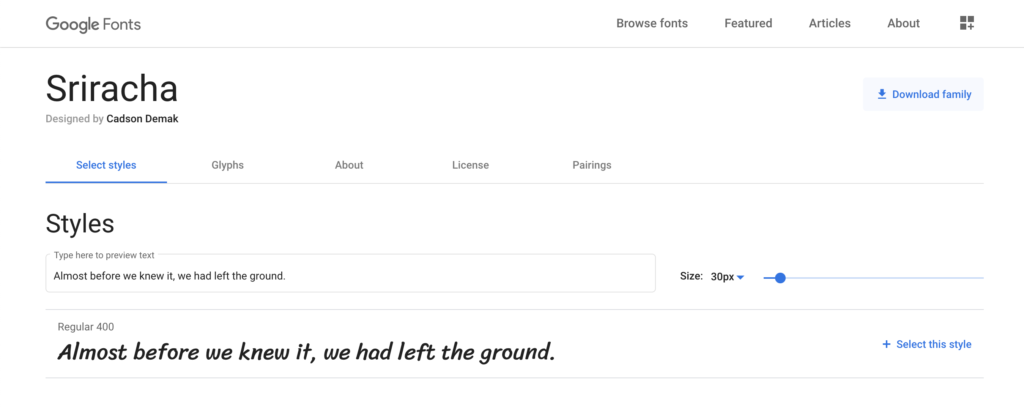
มองหาฟอนต์ภาษาไทยสวย ๆ ใช้งานฟรี นี่เลย…ฟอนต์จาก Google Font ที่มีฟอนต์ภาษาไทยให้เลือกใช้มากมาย วันนี้ทีมงานได้คัดสรรฟอนต์นไทยมาแนะนำให้ชมกันค่ะ เผื่อจะนำไปใช้ประกอบงานส่วนตัว
แนะนำ 8 ฟอนต์ไทยสวย ๆ จาก Google Font คัดสรรมาให้ดาวน์โหลดใช้งานฟรี
ฟอนต์ (Font) ที่จะแนะนำต่อไปนี้เป็นฟอนต์ภาษาไทยที่สวยงาม ดูเป็นมิตร สามารถกับงานส่วนตัวหรือเพื่อการศึกษาได้ฟรี ส่วนงานเพื่อการค้าอาจจะต้องซื้อลิขสิทธิ์ฟอนต์นะคะ
1. Mitr [ดาวน์โหลดที่นี่]
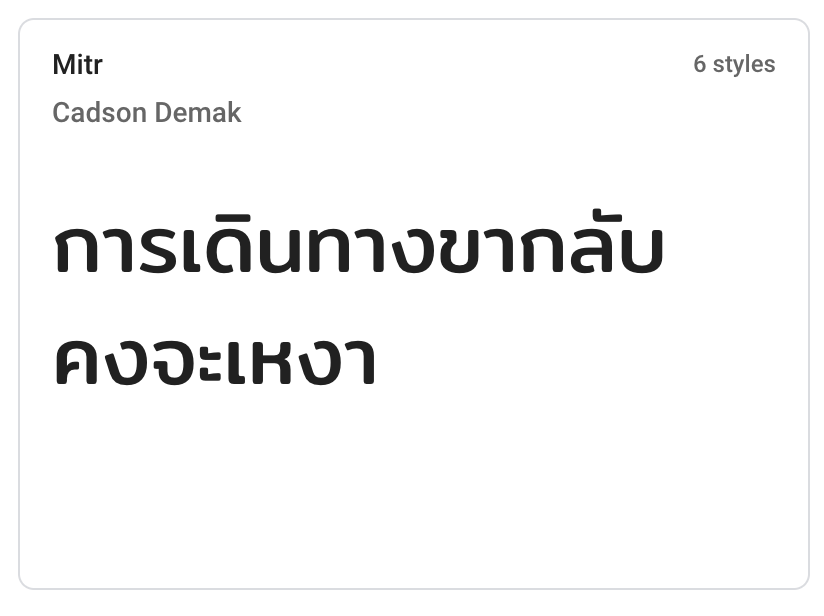
2. Chonburi [ดาวน์โหลดที่นี่]
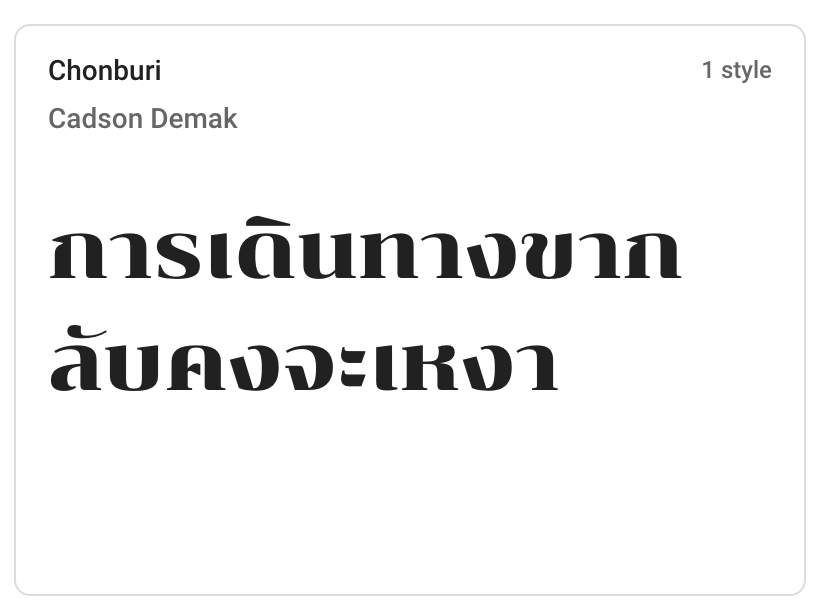
3. Sriracha [ดาวน์โหลดที่นี่]
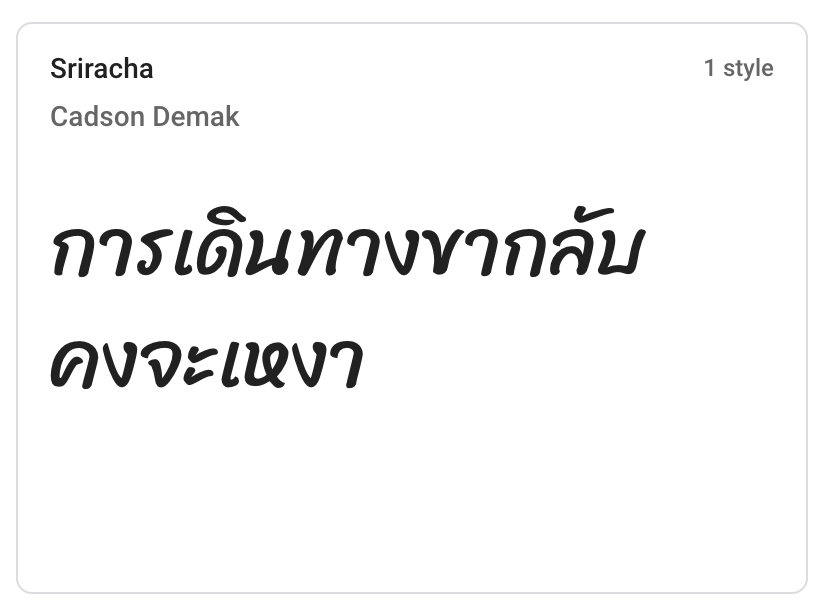
4. Kanit [ดาวน์โหลดที่นี่]
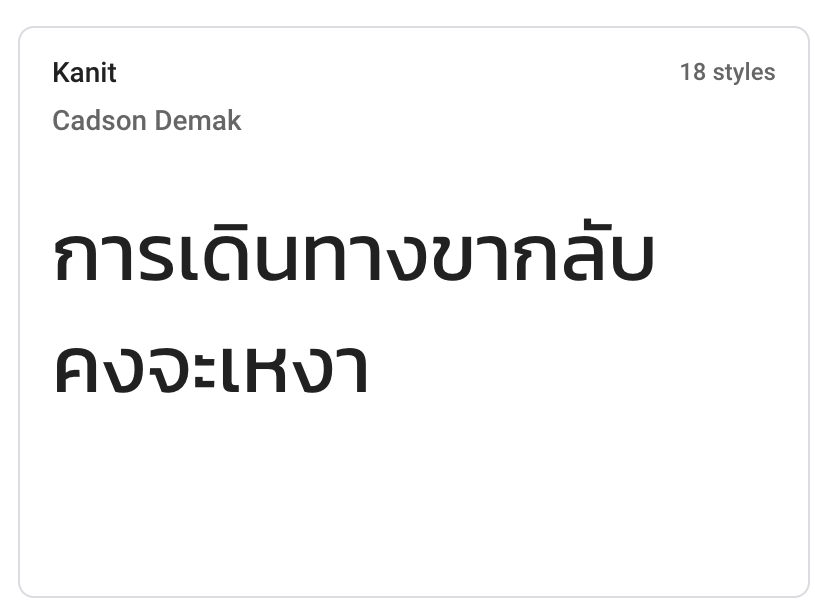
5. Itim [ดาวน์โหลดที่นี่]
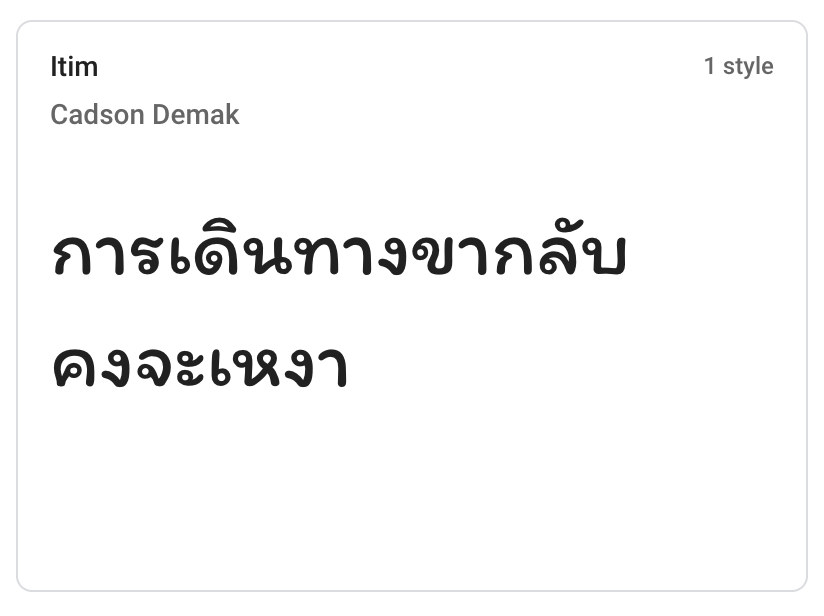
6. Pridi [ดาวน์โหลดที่นี่]
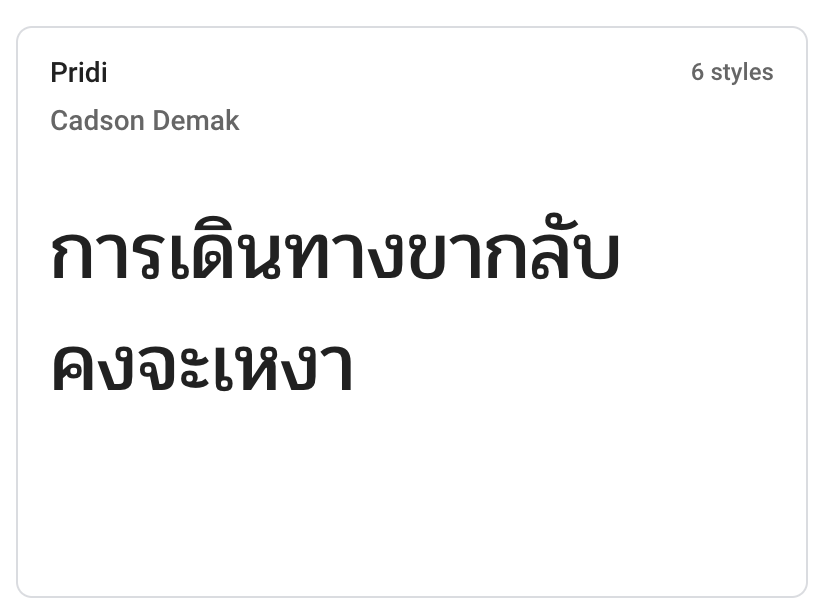
7. Mali [ดาวน์โหลดที่นี่]
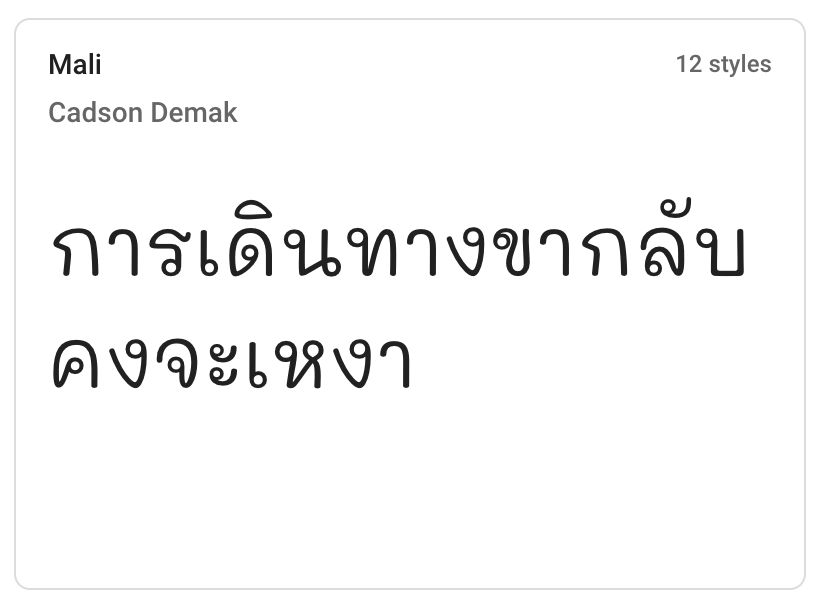
8. Pattaya [ดาวน์โหลดที่นี่]